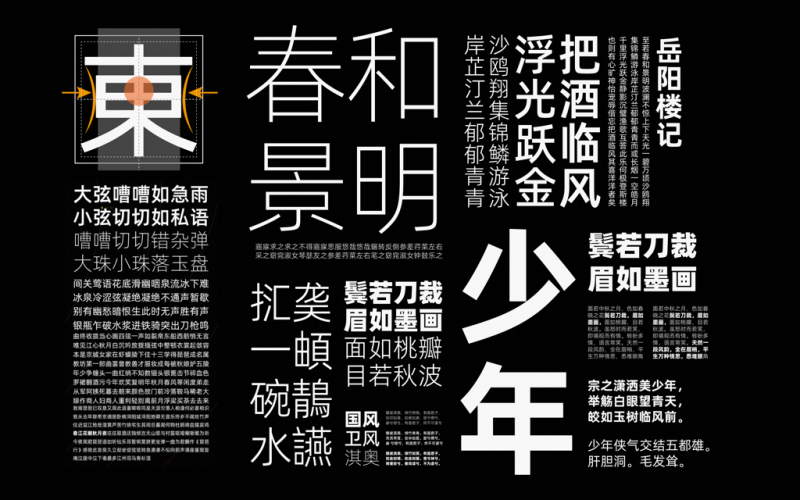
阿里巴巴普惠体四周年:全国互联网企业免费商用字体下载量第一 持续帮助中小企业降本
3月21日,阿里巴巴普惠体四周年主题沙龙在北京举行。2019年4月,阿里巴巴普惠体正式发布。四年来,作为首款由中国企业发布的全场景永久免费商用字体,其官方可统计最小下载量超534万次,在中国互联网企业推出的免费商用字体中保持第一。如果按行业平均的“一年期限”商用字体授权金6000-7000元计算,一年至少可帮助全球中小商家、设计师等群体累计节省320亿元以上。
近期,阿里巴巴率先响应即将推行的新国标,普惠体正在扩容汉字生僻字,已经覆盖姓名、地名、方言、古籍中包含的常用生僻字,成为首批支持汉字常用生僻字全显示的字体,让汉字生僻字更好实现数字化留存与传承。
四年来多次升级,178个语种适用场景广阔
阿里巴巴普惠体项目负责人林江辉介绍,普惠体的设计初衷是为了帮助商家和设计师群体解决字体侵权困扰。一方面,有商家并不清楚很多字体的商用需要获得授权,时而面临高额侵权赔偿;另一方面,一些字体的商用授权成本对中小商家而言比较高。因此,2019年4月,历时10个月的设计和准备,阿里巴巴普惠体1.0正式上线,覆盖全球173个语种,面向全社会开放下载,在所有平台均可永久免费商用。
推出后,普惠体就以通用、开放、普适的特征受到用户的喜爱,由于它没有过于强烈的字形风格,而重在提供丰富的字重、语种等实用选择,因此能够适配广阔的使用场景。
2021年5月,普惠体2.0发布,中文版优化了部分字体结构,外文字体新增了泰文和越南文,语种拓展至175个,外文字体设计也更符合当地的阅读习惯与文化。2022年,普惠体再次更新,新增繁体中文、日文、韩文,至此已覆盖全球178个语种,囊括当前全球大部分重要市场,并推出版权检测工具,进一步帮助在全球做生意的中小商家用字无忧。
林江辉用“螺蛳壳里开道场”来形容普惠体的设计过程。为了在手机屏幕的有限空间尽可能丰富呈现,设计师们不断和细节较劲,让字体更简洁清晰,同时提升阅读文字的流畅感。四年以来,项目组也不断调研和听取用户的反馈,结合真实需求来改进设计,比如调整笔画结构、缩小标点间隙、增加字重,从而适用更多场景。
率先响应新国标进行字体扩容,让汉字生僻字更好在数字时代留存
2023年8月1日,新版《信息技术中文编码字符集》强制性国家标准将正式实施,比上一版增加录入了1.7万余个生僻汉字。此前,许多生僻字由于尚未数字化,无法在信息系统中通用。为此,普惠体项目组提前进行字库扩容,目前完成的汉字扩容量已满足新国标(GB18030-2022)3档强制性实现级别中的级别1和2,其中包含绝大部分人名、地名、方言、古籍中的生僻字,成为国内首批覆盖常用生僻字的免费商用字体。
“项目组正在全力向实现级别3冲刺,预计于6月1日完成并正式更新,”林江辉表示,“希望普惠体能帮助生僻字在数字时代不再寸步难行,让古老的汉字焕发新光”。
在四周年主题沙龙现场,知名书籍设计师、南京师范大学文化研究中心主任朱赢椿也表达了他对普惠体的期待。在朱赢椿看来,好的设计意味着平衡了商业与艺术的关系。他认为,普惠体很好地保持了普惠理念,也兼顾了设计之美,还为汉字的数字化留存提供了很好的解题思路,无论从实用价值还是文化传承的角度看,都有值得借鉴之处。
永久免费商用,持续降低中小商家经营成本
截至目前,普惠体官方平台可统计最小下载量超534万次,而实际使用者更是不计其数。按行业平均的“一年期限”商用字体授权金6000-7000元计算,一年至少可帮助全球中小商家、设计师等群体累计节省320亿元以上。如果按照永久商业授权金计算,则能够节省更多。
普惠体也带动了阿里生态业务广泛参与到为全社会提供免费字体的行列中。例如,阿里妈妈推出了“阿里妈妈数黑体”,满足商家对美术标题字的需求;阿里健康推出了“阿里健康体”,为医院、药店提供更贴合患者感受的圆体字;钉钉则联合汉仪字库推出了“钉钉进步体”,兼具数字科技感和“让进步发生”的品牌主张。
林江辉说,“从诞生起,阿里巴巴普惠体就希望通过开放免费、专业的商用字体,惠及全球中小商家、设计师群体、内容创作者。未来,普惠体会秉承这一初衷继续走下去,带动更多参与者一起,用普惠设计让商业美而简单。”